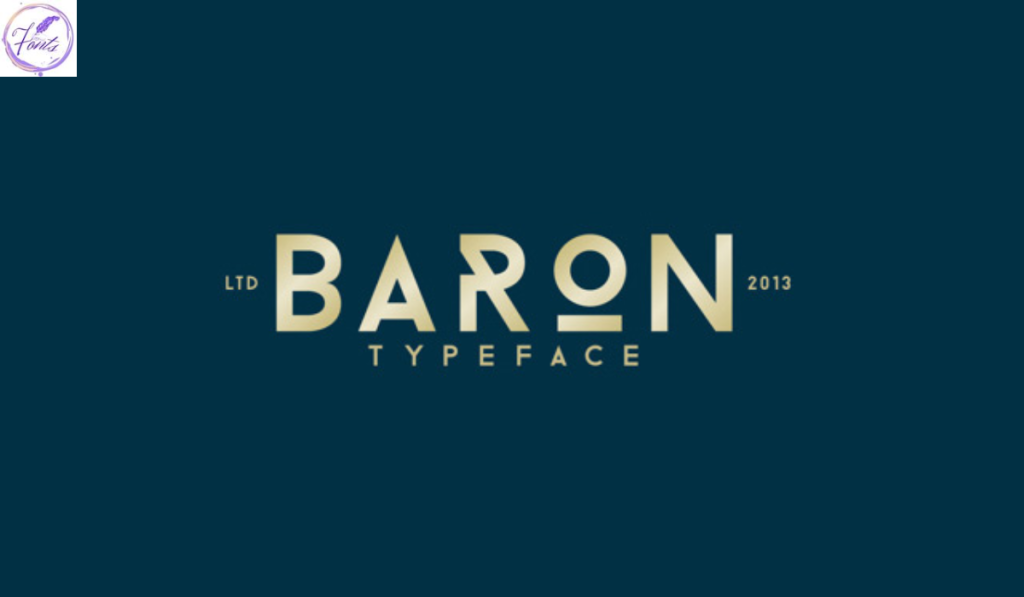
Font Baron việt hóa
Tác giả: Frank Hemmekam
Ngày phát hành: 2013
Ngôn ngữ: Tiếng Việt, Tiếng Anh, và nhiều ngôn ngữ khác
Bộ Font: Baron Neue
Phân loại: cá tính, độc đáo
Kiểu chữ: sans serif
Độ dày: Regular, Bold, Black, Italic
Font Baron là một font chữ độc đáo và hiện đại, được thiết kế để mang lại sự mạnh mẽ và nổi bật cho các dự án thiết kế. Ra mắt vào năm 2013, font này được tạo ra bởi nhà thiết kế Frank Hemmekam và nhanh chóng trở nên phổ biến trong cộng đồng thiết kế. Với các đường nét đậm và góc cạnh, font Baron tạo nên sự chuyên nghiệp và phong cách cho bất kỳ ấn phẩm nào. Đặc biệt, font này đã được Việt hóa đầy đủ, giúp bạn dễ dàng sử dụng trong các dự án tiếng Việt mà không gặp bất kỳ vấn đề nào về ký tự.
Đánh giá font baron
Font Baron đã nhận được nhiều lời khen ngợi từ các nhà thiết kế đồ họa và chuyên gia trong ngành. Nó không chỉ mang lại vẻ đẹp mạnh mẽ và hiện đại, mà còn rất dễ đọc và ứng dụng linh hoạt trong nhiều loại dự án khác nhau. Tạp chí thiết kế nổi tiếng “Creative Bloq” đã xếp hạng font Baron là một trong những font chữ đẹp và ấn tượng nhất cho năm 2012. Với khả năng hiển thị tốt trên cả màn hình và bản in, font này là lựa chọn lý tưởng cho các thiết kế từ poster, banner đến các tài liệu quảng cáo.